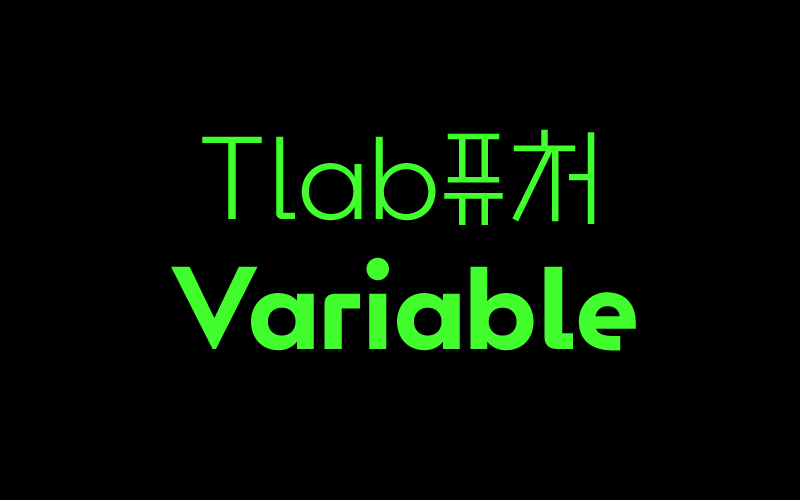
TlabFutureVariable
1 Style - VariableTlab퓨처 베리어블은 기하학적 조형과 본질적인 획으로 한글의 형태를 강조한 서체입니다. 정원의 구조를 유지한 ‘ㅇ’ 자형과 자소마다 다른 자폭의 리듬을 통해 고유한 균형감을 형성합니다. Variable 폰트 확장을 통해 Light부터 Bold까지 4단계 굵기를 유연하게 표현하며, 형태의 일관성과 새로운 가능성을 동시에 담아냅니다.